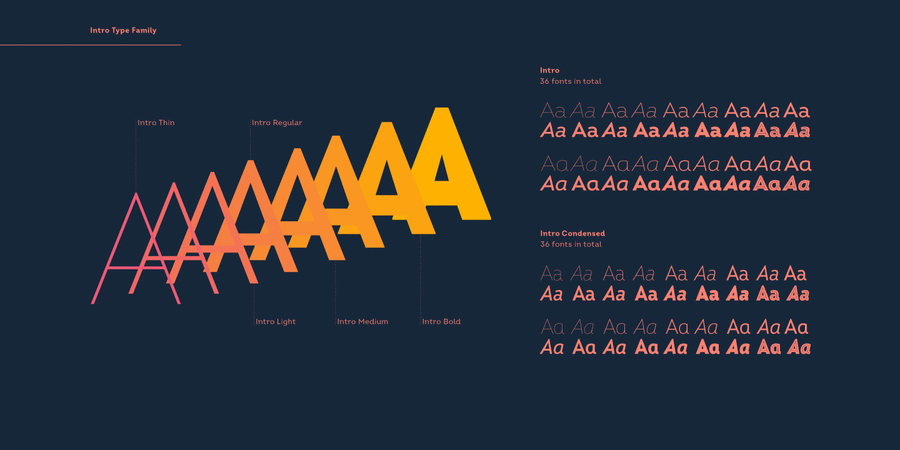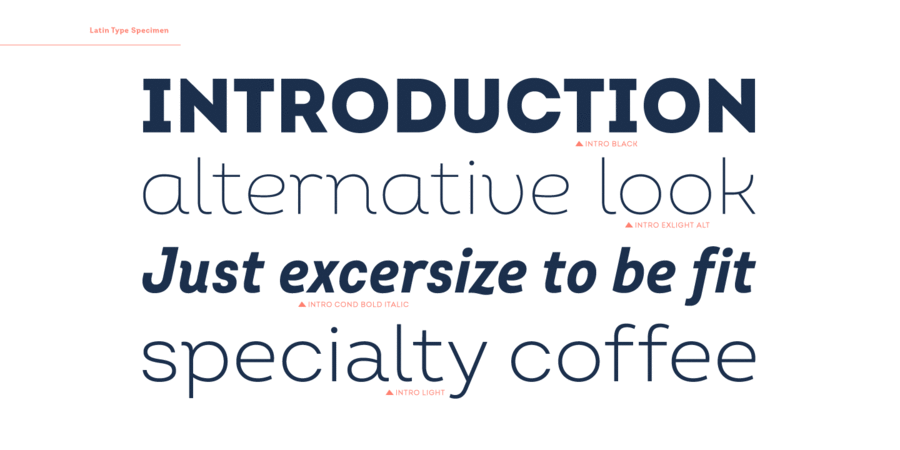
Intro (72 шрифта)
Наступне велике оновлення шрифтового сімейства Intro містить низку суттєвих покращень цього стильного сучасного гротеску. На додаток до повністю переглянутого розподілу ваг, набір містить 2 нові ваги та відповідний курсив, загалом 8 ваг і 72 шрифти, 22 шрифти додатково! Грайливість Intro була ще більше підкреслена додаванням деяких спеціальних інгредієнтів, включаючи ретельно відрегульовані прямі курсиви, поруч з існуючими прямими накресленнями. Усі накреслення доступні у звуженій версії, а крім того, ми додали 3 додаткові декоративні накреслення, з якими ви можете погратися. Fontfabric спроектували розширений набір гліфів, який охоплює розширену латиницю та кирилицю з відповідною мовною локалізацією. Всі функції OpenType переписані і тепер дозволяють використовувати чутливі до регістру форми і контекстні альтернативи, а також безліч стилістичних альтернатив. Стандартний набір цифр також охоплює табличні пропорції та символи, вищі та нижчі, чисельники та знаменники, а також дроби. Доступні 4 безкоштовних накреслення Intro. Функції OpenType: стилістичні альтернативи, контекстуальні альтернативи, локалізовані форми, табличні цифри, діагональні дроби, знаменник, чисельник, підрядкові індекси, надрядкові індекси, чутливі до регістру індекси. Шрифт розроблений Светославом Сімовим у 2019-2020 роках.
Асоціації з сімейством шрифтів IntroОсобистість і характер гарнітури:
делікатний, чистий, легкий, прохолодний, модний, тонкий, сучасний, якісний, невагомий, прозорий, інтимний, крихкий, ніжний, повітряний, скляний, дротяний, худий, гнучкий, динамічний, міський, ясний, гладенький, оригінальний, добрий, приємний, свіжий, затишний, неоновий, пластичний, сексуальний, рівний, точний, М'який, комфортний, зручний, технічний, ввічливий, зрозумілий, домашній, смачний, сімейний, мотивуючий, помітний, яскравий, стійкий, сильний, важкий, виразний, хіпстерський, дерев'яний, молодіжний, дзвінкий, святковий, радісний, позитивний, гострий, вінтажний, переконливий, твердий, добротний, міцний, залізний, доступний, екологічний, ефектний, теплий, ламповий, крафтовий, осінній, гарячий, артистичний
краса, туалетна вода, косметика, мода, дієта, гігієна, чистота, парфумерія, дизайн, лосьйон, АСМР, шампунь, перукарня, Інстаграм, одяг, взуття, інтер'єр, вода, здоров'я, екологія, йога, небо, торгівля, дім, родина, кухня, їжа, меблі, кафе, ресторан, обід, автобус, шоу, телебачення, розваги, аксесуари, бар, відпочинок, атракціон, прикраса, свято, коктейль, Місто, продукти, м'ясо, тесля, деревина, хенд мейд, закуска, крамниця, фермер, піцца, печиво, вечеря, гамбургер, осінь Гарнітура має ознаки стилів: